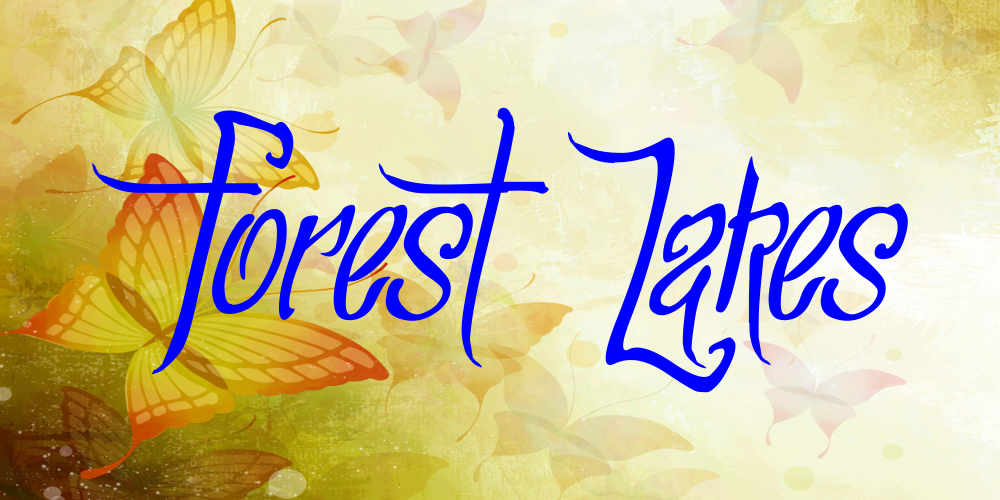
Forest Lakes font
Aqui está uma descrição em português para a página de download da font “Forest Lakes”, adequada aos parágrafos solicitados: A font “Forest Lakes” é perfeita para aqueles que buscam um visual suave e elegante, projetada para combinar bem com qualquer estilo gráfico. Inspirada na harmonia do arco-íris sobre a superfície de um lago cristalino, esta fonte tem uma textura fluida e delicada, que traz um toque natural à sua criação. Desenvolvida pelo designer Hamilton, a “Forest Lakes” é perfeita para uso em projetos gráficos como design de logos, editoriais de revistas ou até mesmo websites. Com uma base de desenho ajustada, esta fonte oferece um contraste visual atraente e é particularmente adequada para aplicativos que valorizam a simplicidade e o equilíbrio. A “Forest Lakes” tem sido criada não apenas para agradar aos olhos, mas também para facilitar as tarefas cotidianas de quem trabalha com design. Essa fonte é especialmente adequada para textos longos e para grandes tamanhos de texto sem comprometer a legibilidade. O visual suave e natural da “Forest Lakes” é uma excelente escolha para aqueles que desejam criar um ar fresco, ao mesmo tempo que mantêm o foco do design no conteúdo. Com certeza, esta font será a pedida perfeita para designers amadores e profissionais, proporcionando um toque único em suas produções gráficas.